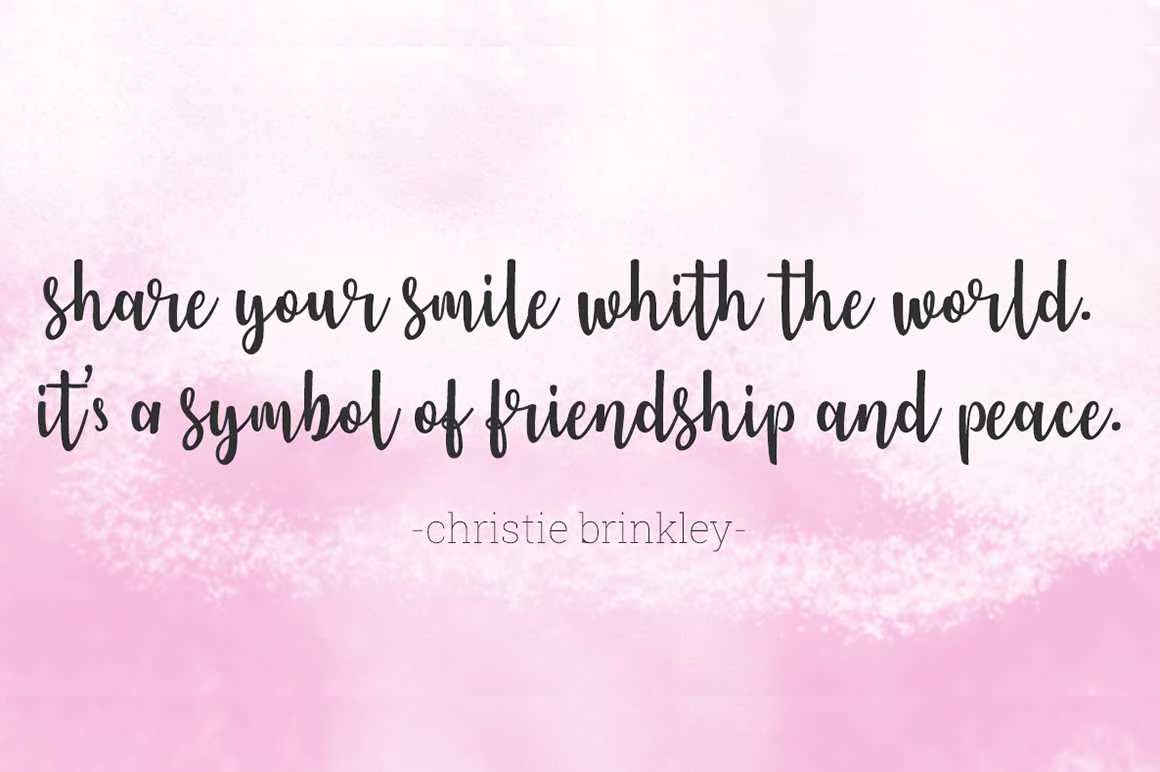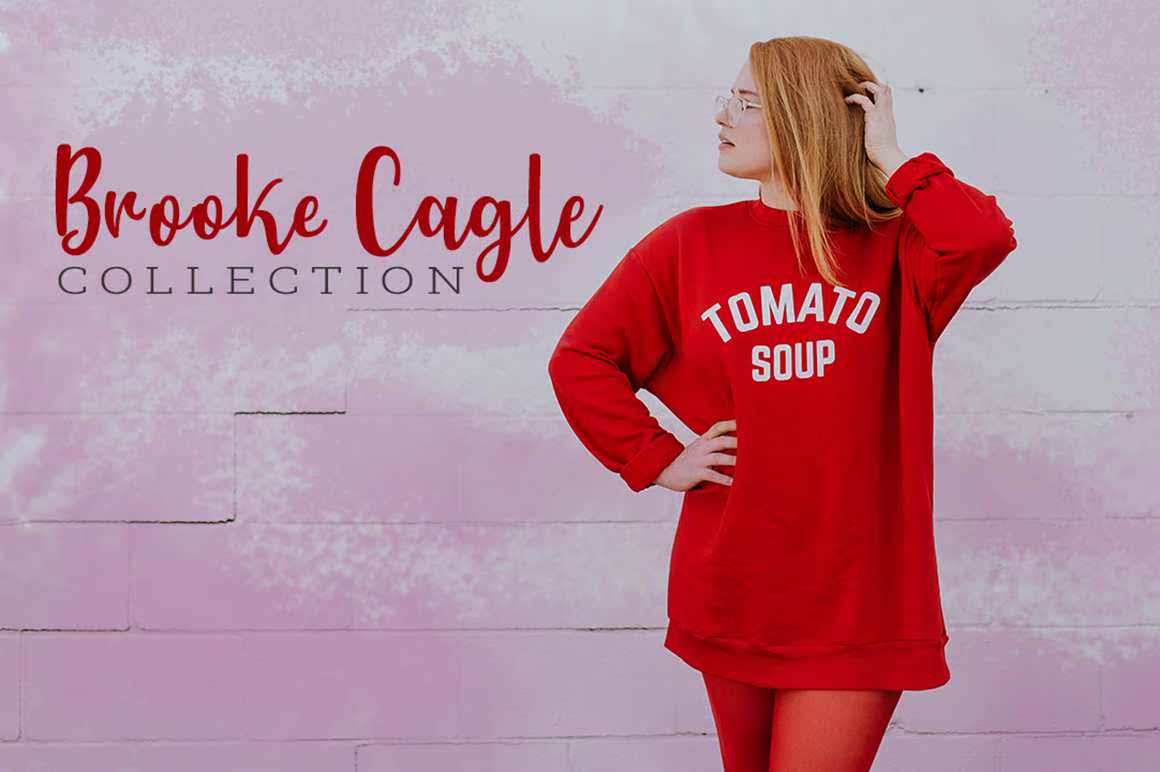
简介:Jeniverellis将钢笔刷成整洁的笔画。像封情书一样,光滑、干净、简单。Jeniverellis对婚礼、活动、请柬、护送卡、桌号、报价、展示、徽标、博客幻灯片、特色服饰、邮票、包装、问候卡等都有影响,Jeniverellis使钢笔刷的颜色变得整洁。像情书一样,光滑、干净、简单。Jeniverellis对婚礼、活动、请柬、护送卡、桌号、报价、展示、徽标、博客幻灯片、特色服饰、邮票、包装、问候卡等都有影响。